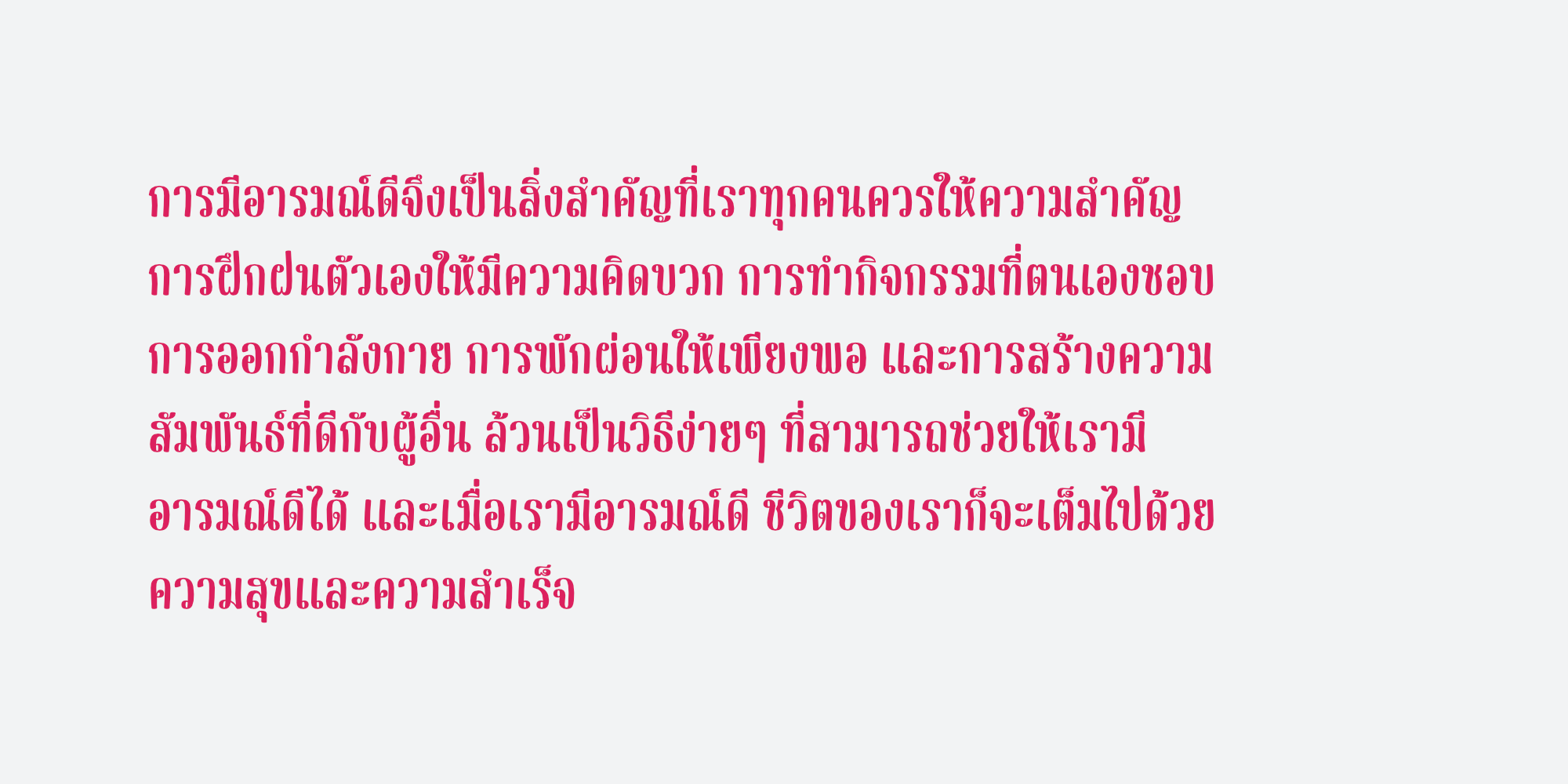
อารมณ์ดี | Aromdee
ชื่อฟอนต์ : อารมณ์ดี | Aromdee
อารมณ์ดี เป็นแบบอักษรพาดหัวสไตล์ลายมือ เหมาะสำหรับสื่อประชาสัมพันธ์ที่เป็นกันเองสบาย ๆ แบบอักษรนี้มี 1 รูปแบบ โดยรองรับทั้งชุดอักษรลาติน 1 และอักษรไทย
Creator : อานุภาพ ใจชำนาญ (Anupap Jaichumnan)